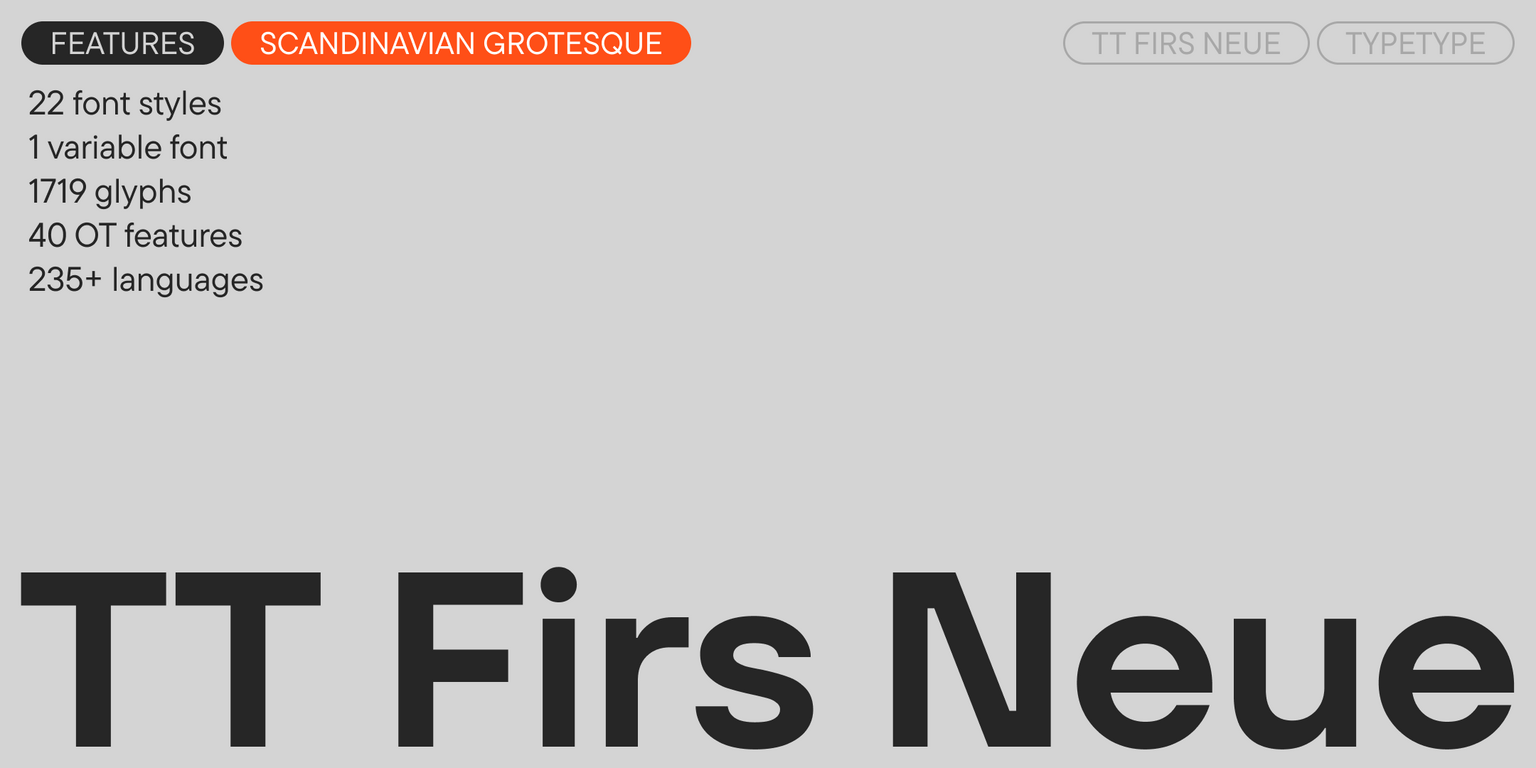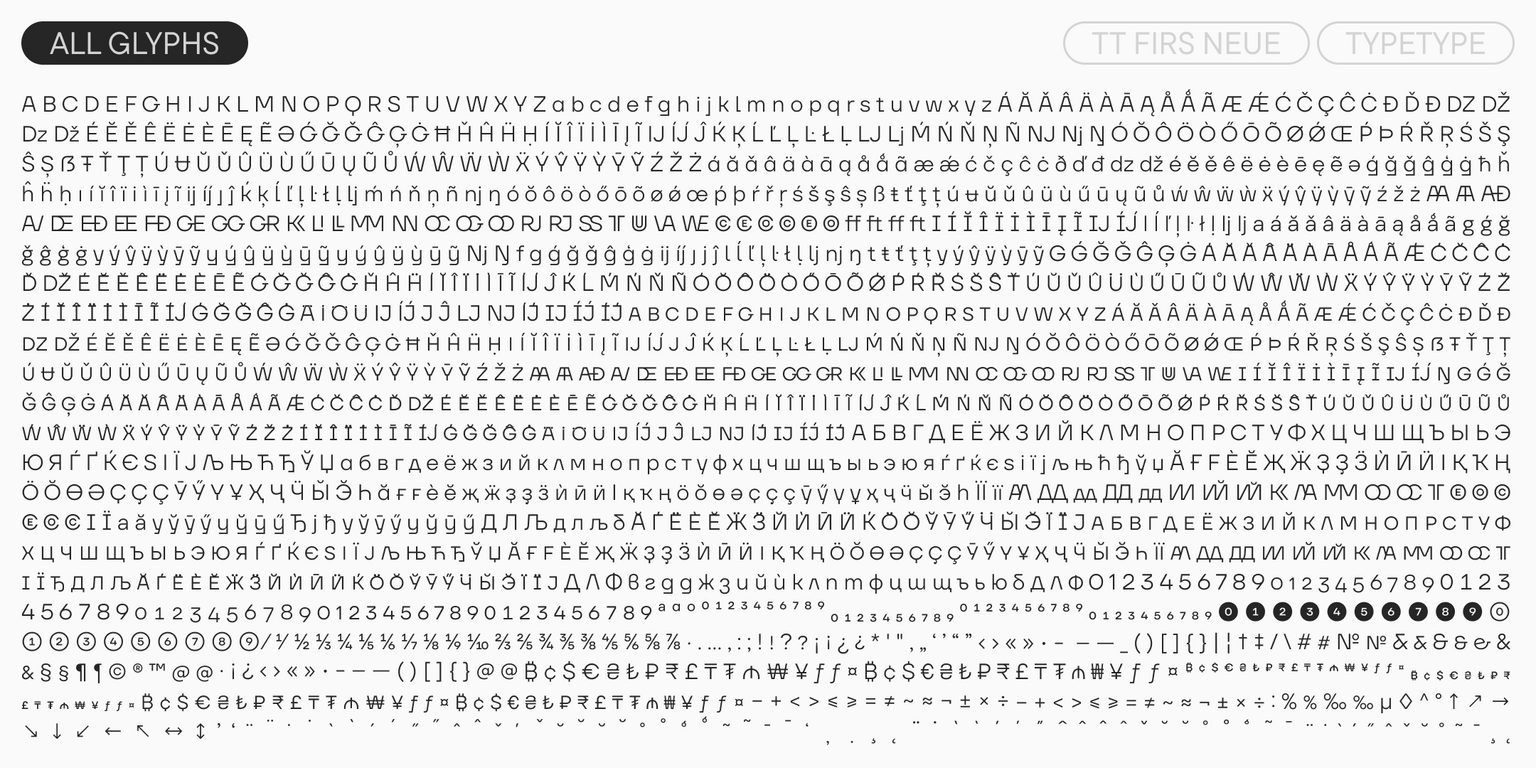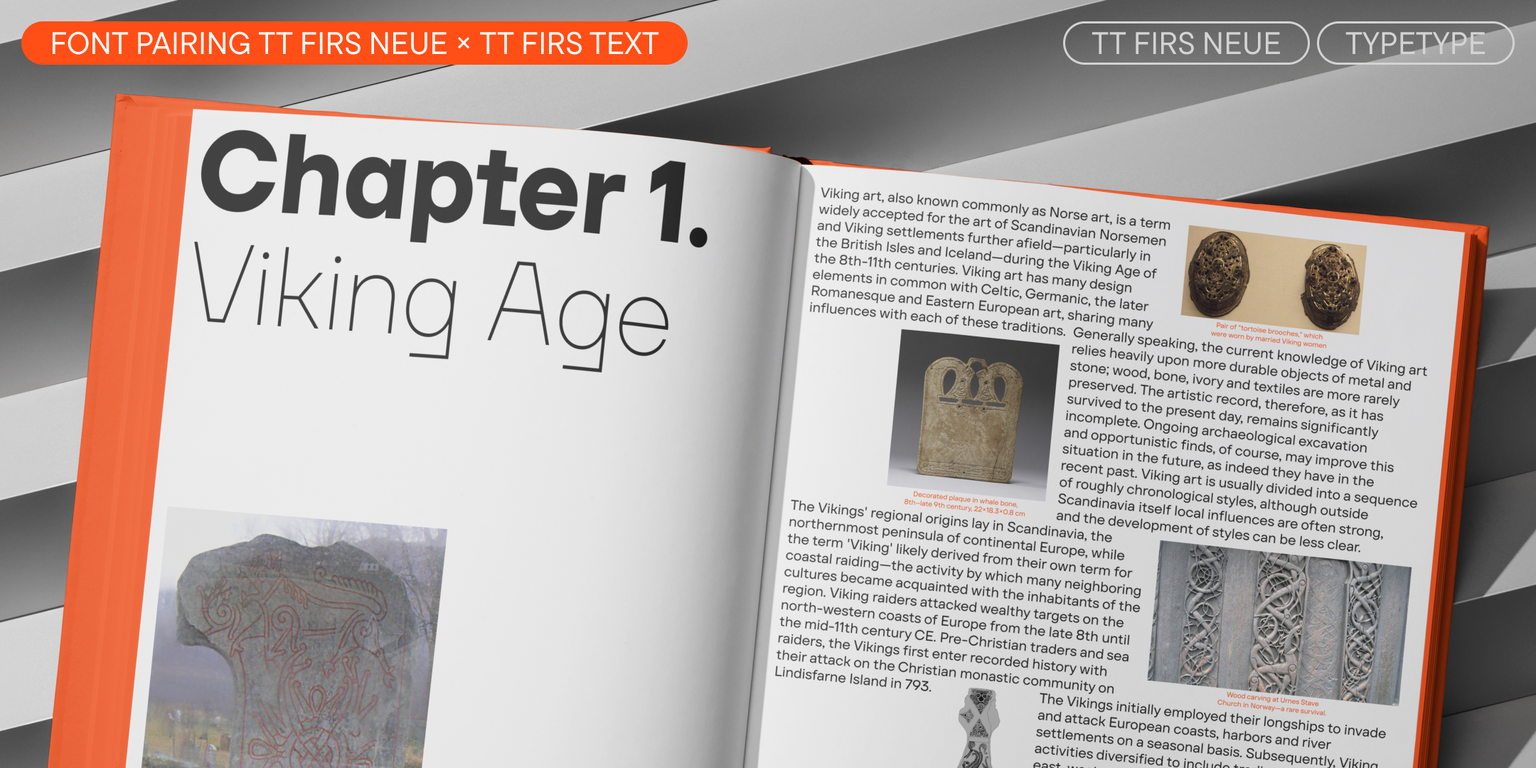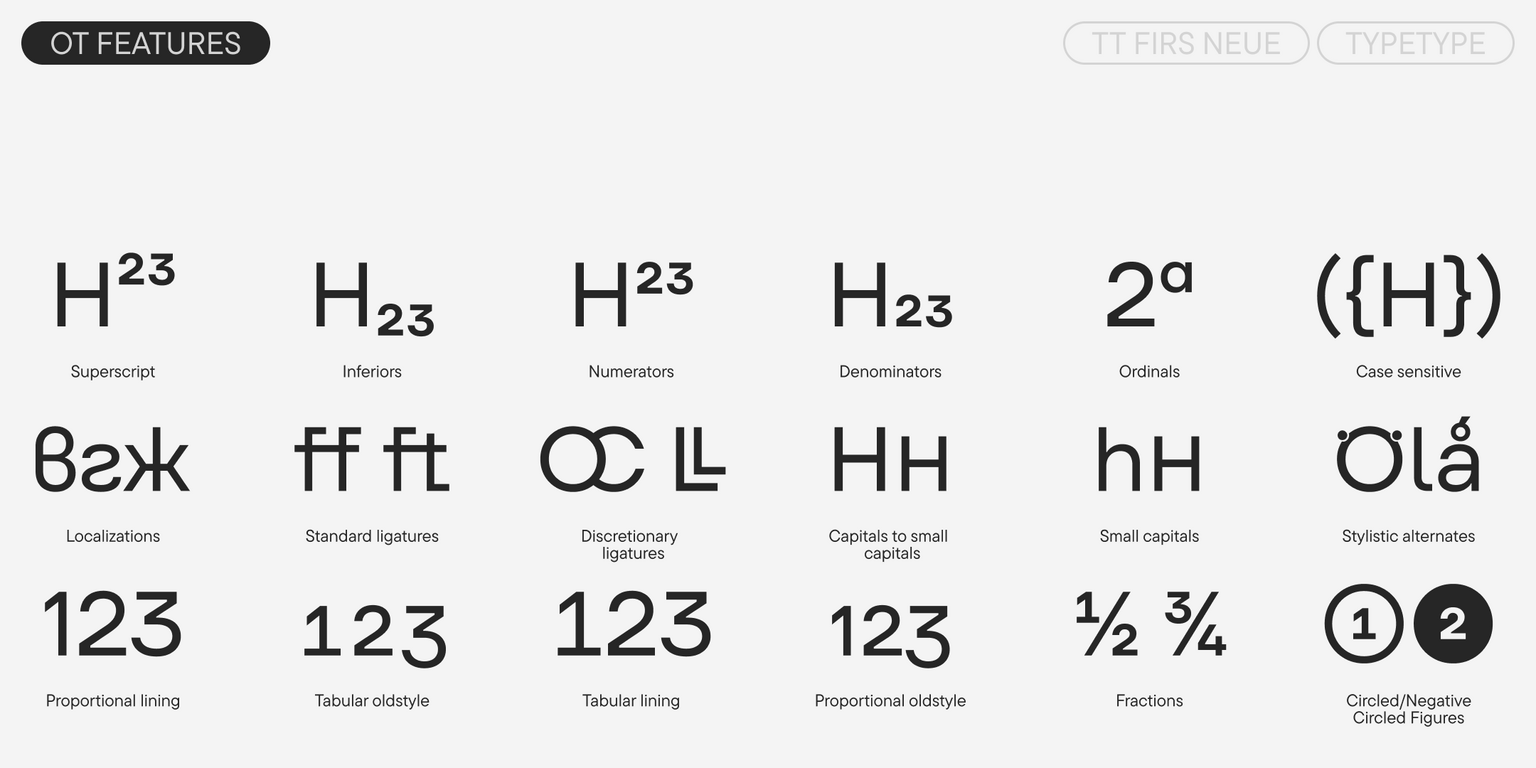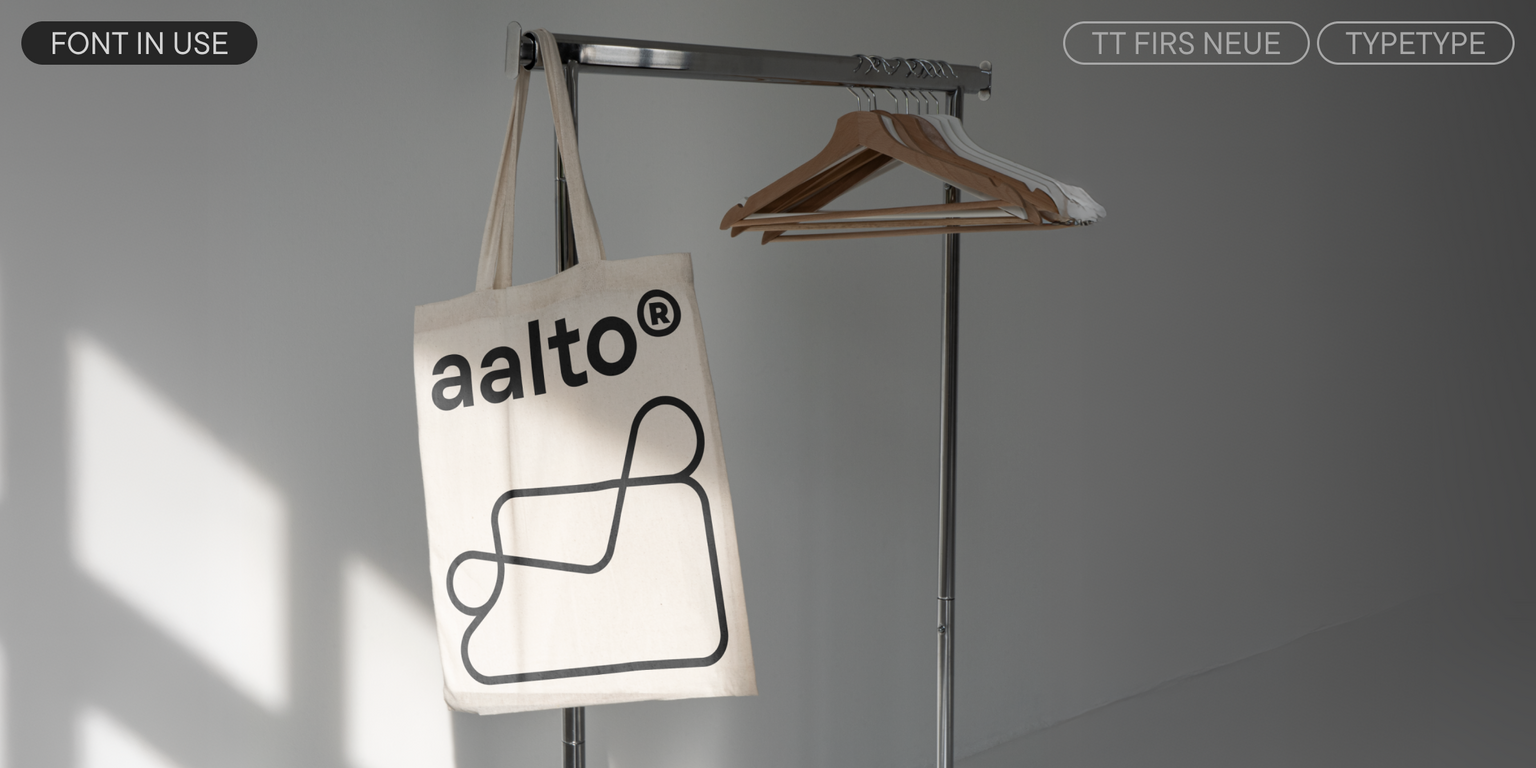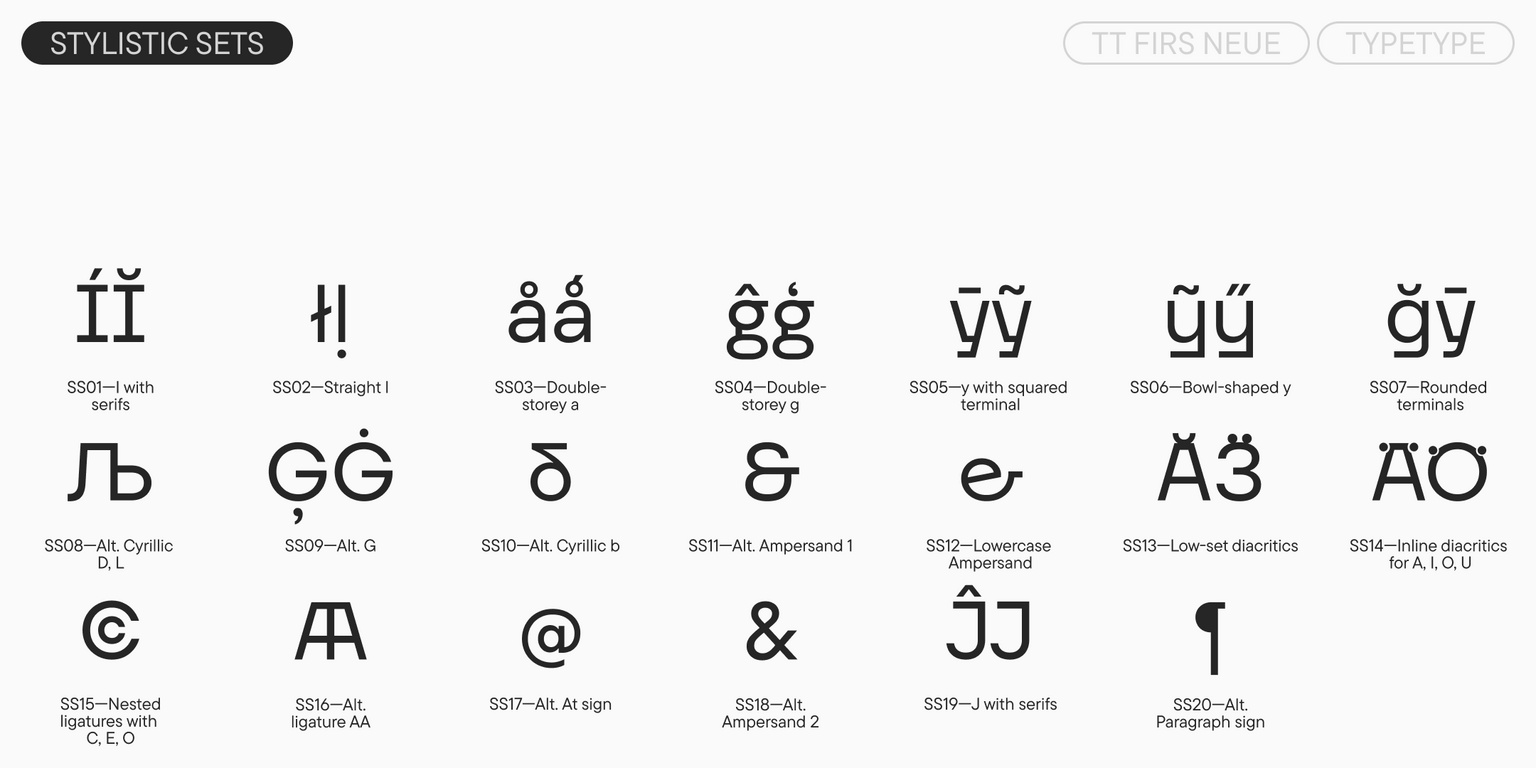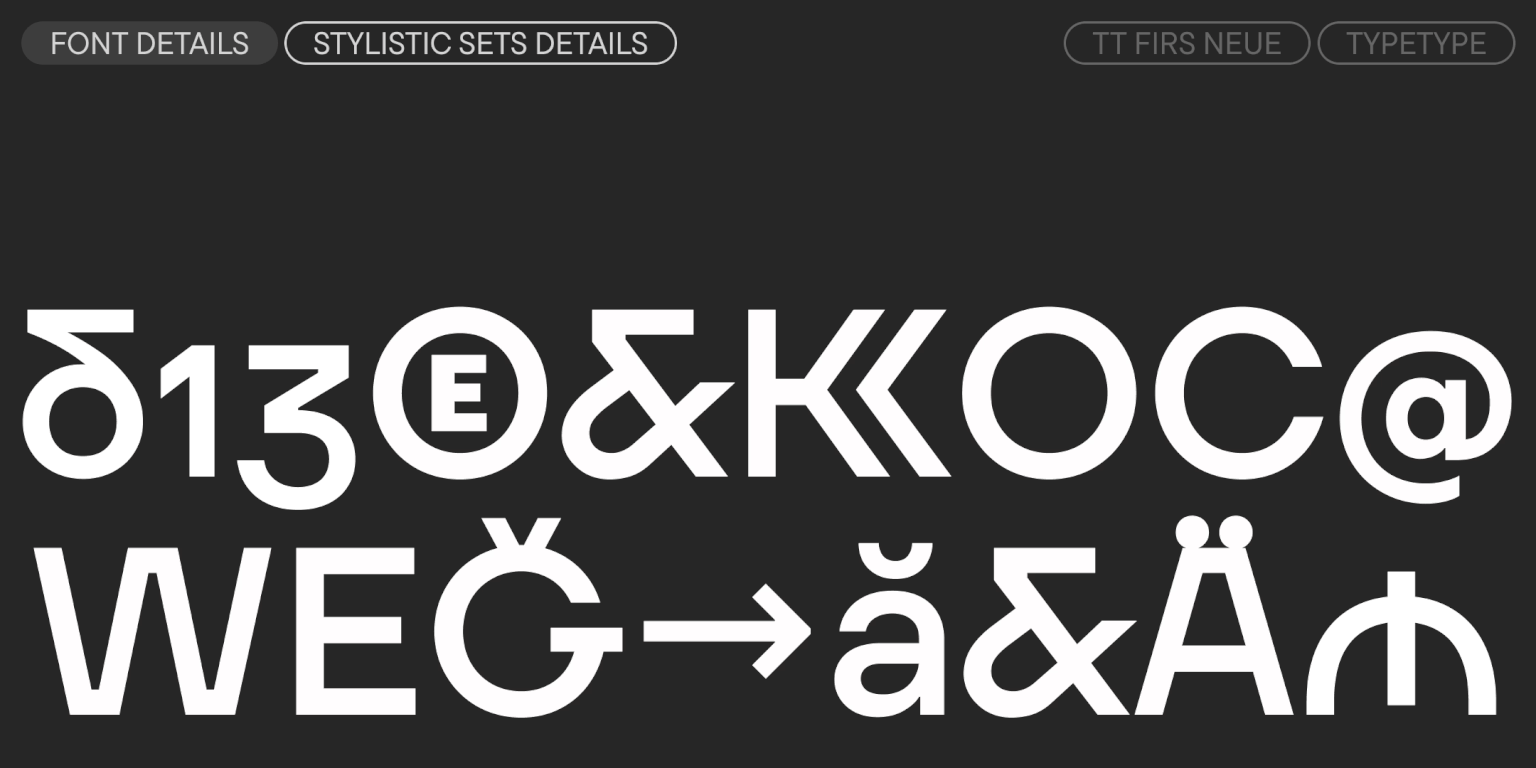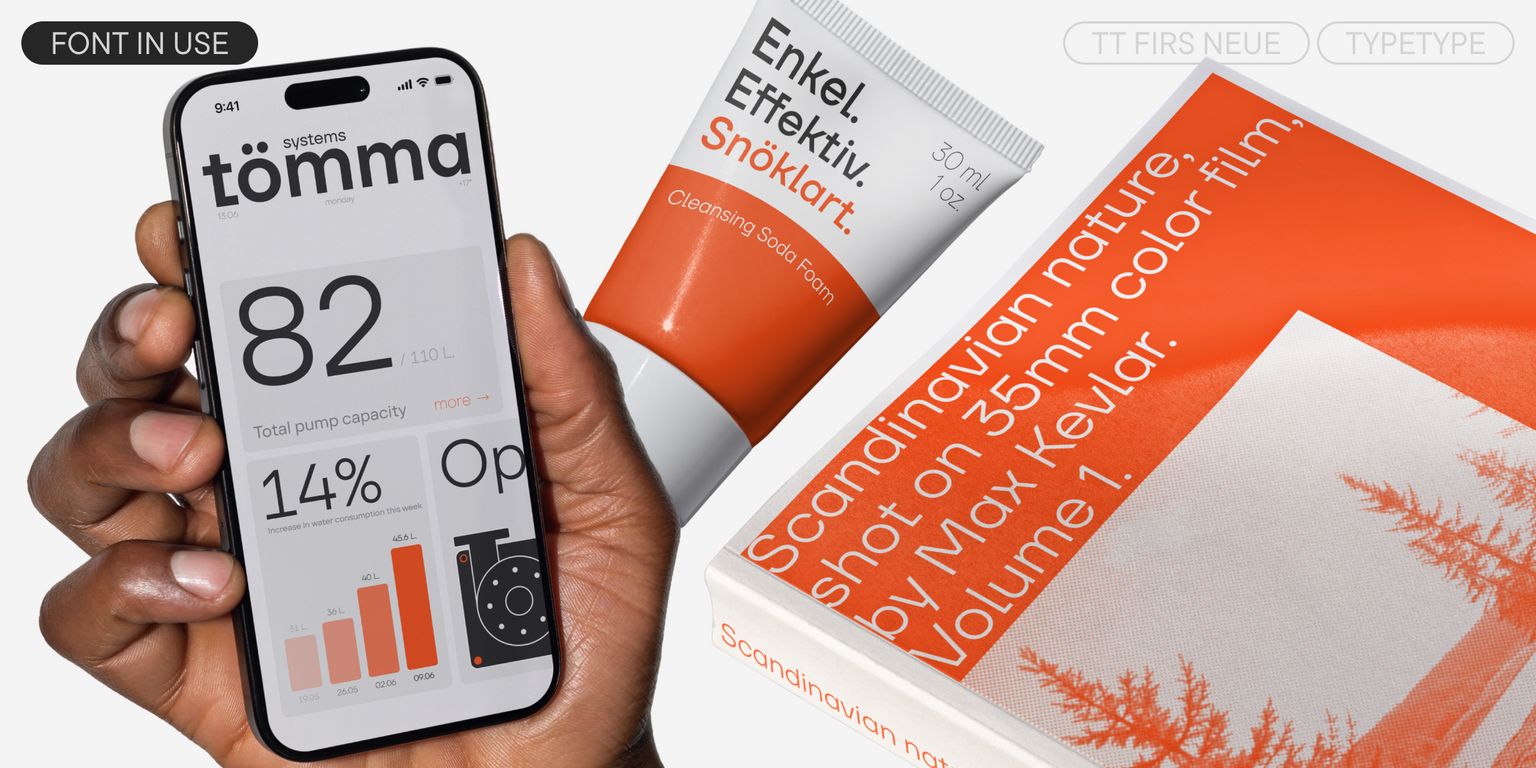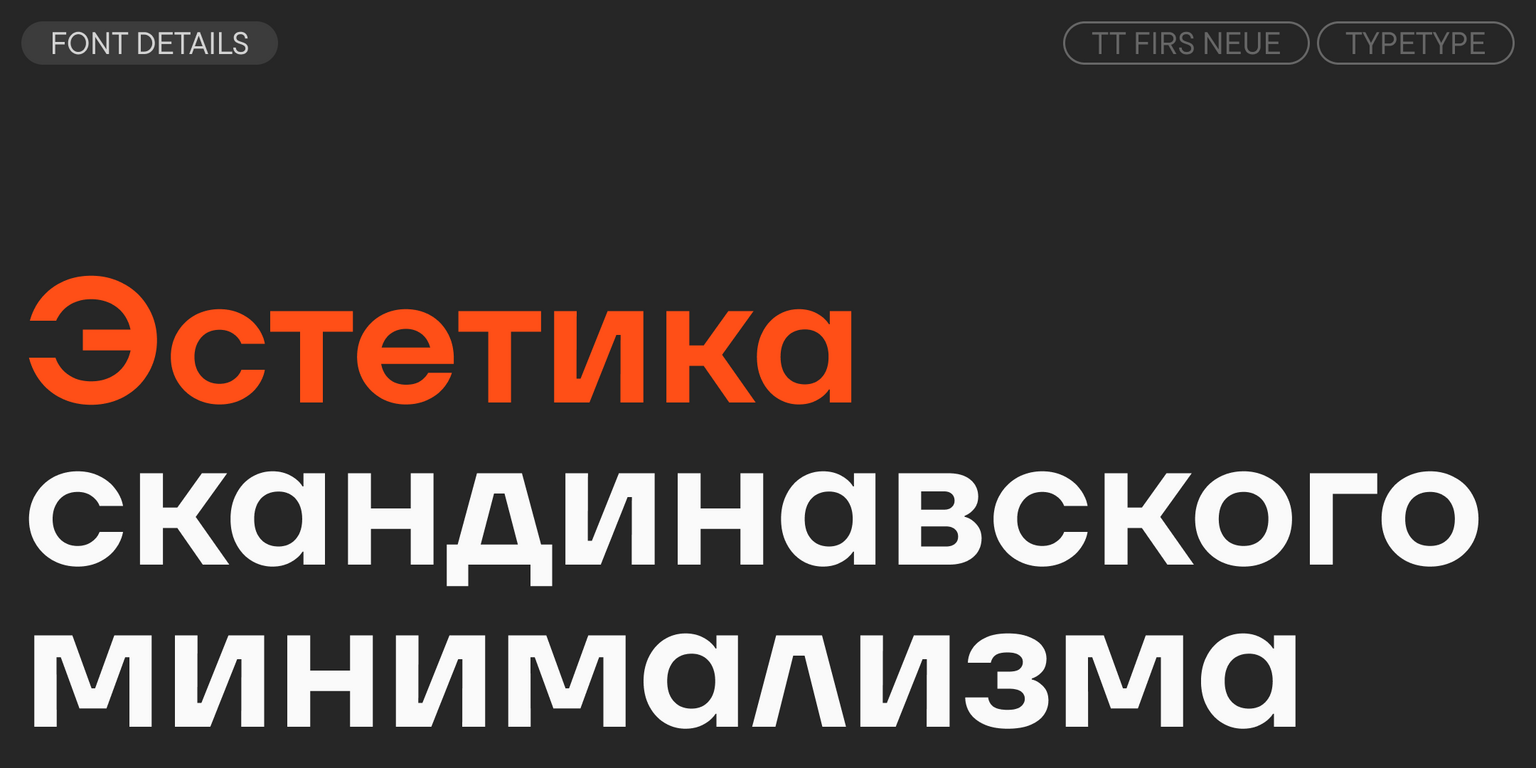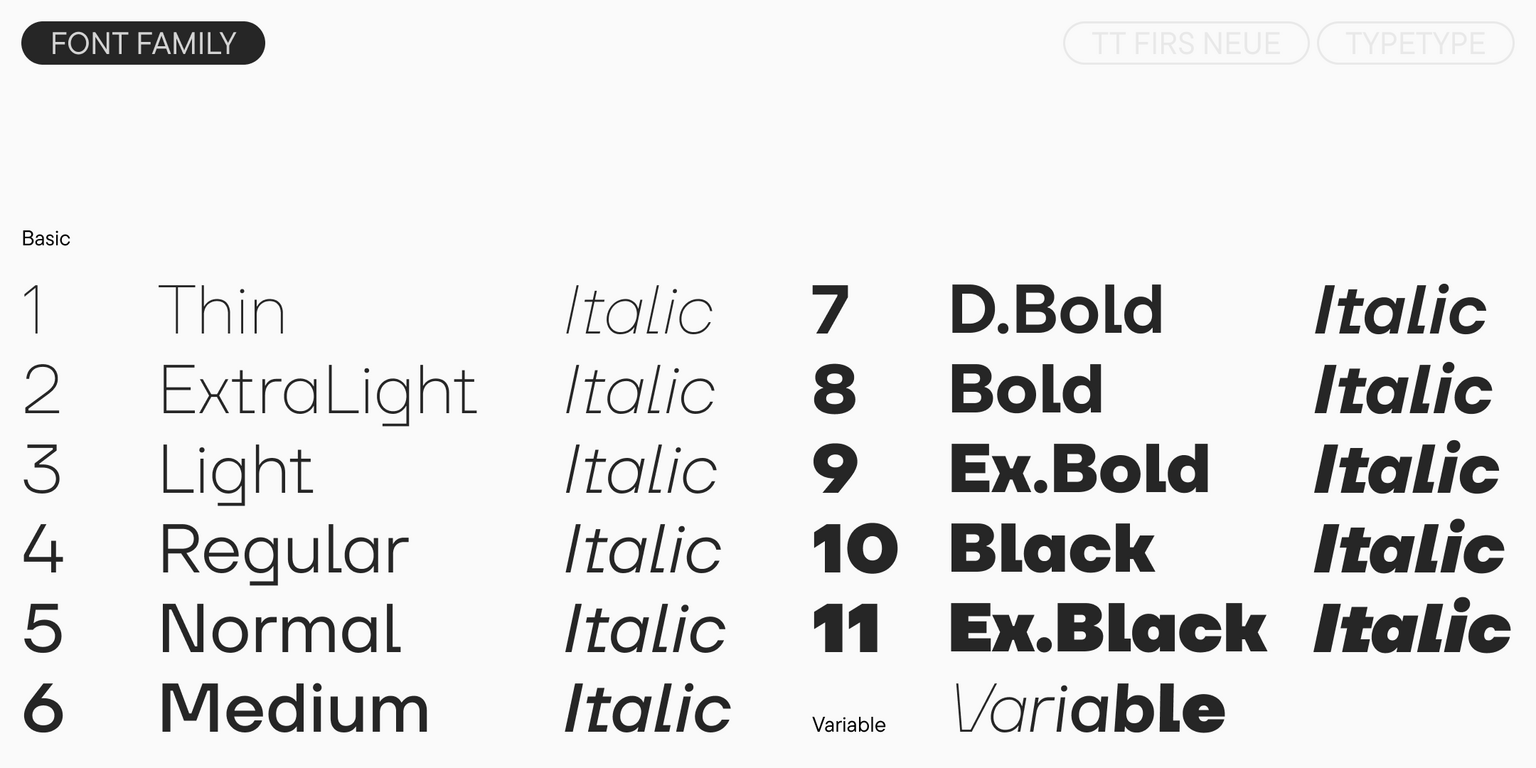
TT Firs Neue
TT Firs Neue — ТТ Фирс Нью
Произносится «ТТ Фирс Нью». «Фирс» — производное слово от fir, в переводе с английского «ель». «Neue» — в переводе с немецкого «новый». Буквы «TT» являются аббревиатурой названия компании.
TT Firs Neue — сбалансированный гротеск со скандинавскими мотивами. Это выразительный и привлекательный, при этом лаконичный и универсальный в использовании шрифт.
TT Firs Neue
TT Firs Neue — скандинавский гротеск с уникальными графическими элементами
TT Firs Neue
TT Firs Neue 2.0 берет свое начало в 2015 году, когда мы решили выпустить шрифт без засечек в скандинавском стиле под названием TT Firs. Три года спустя, в 2018 году мы переосмыслили и выпустили новую версию семейства шрифтов под названием TT Firs Neue. Вот лишь некоторые особенности нового семейства: более ярко выраженные акцидентные элементы шрифта, более крупные строчные символы и расширенный набор символов. После оглушительного успеха шрифта, в 2023 году, мы создали TT Firs Neue заново. В нем больше начертаний, набор символов увеличился вдвое, контуры и OpenType фичи стали более проработанными.
TT Firs Neue
Геометрический, самобытный, уникальный, универсальный
TT Firs Neue
Мы сделали совершенно новые италики
TT Firs Neue в дизайне
О гарнитуре TT Firs Neue
Встречайте TT Firs Neue версии 2.000 — скандинавский гротеск нового поколения!
TT Firs Neue — сбалансированный скандинавский гротеск с брутальным нордическим характером. Это узнаваемый и привлекательный шрифт, в котором выразительные графические элементы сочетаются с универсальностью использования. С момента выхода гарнитура приобрела огромную популярность среди дизайнеров, поэтому мы переиздавали её дважды — чтобы довести до совершенства. Подробную историю создания и развития TT Firs Neue рассказывали в статье.
Перед работой над обновлением мы провели масштабное визуальное исследование, чтобы сделать акцидентные детали привлекательными, а характер гарнитуры ещё более гармоничным. Так, визуальные компенсаторы в шрифте однородны по логике, а формы круглых знаков и знаков с полуовалами единообразны во всех начертаниях. Знаки с диагоналями, треугольные знаки и терминалы также приведены к единой логике. Шрифт выглядит консистентно и стилистически выверенно.
Также мы провели исследование по скандинавским языкам: это помогло создать аутентичные лигатуры и диакритические сеты, которые действительно будут полезны дизайнерам. Диакритика, цифры и знаки пунктуации придерживаются одной логики и способствуют гармоничному восприятию шрифта.
TT Firs Neue поддерживает большое количество полезных OpenType фич, в том числе альтернативные формы знаков. Также в гарнитуру входит вариативный шрифт, меняющийся по двум осям — жирности и наклону. Всё это позволяет подстраивать шрифт под свои задачи, открывая его с новых сторон.
TT Firs Neue — это шрифт-бестселлер, который пользуется большой популярностью, в том числе в европейском брендинге. Его можно увидеть в музеях, архитектурных бюро, кофейнях — он отлично вписывается в скандинавскую эстетику. TT Firs Neue может быть заголовочным или использоваться для фрагментов текста, подойдёт для брендинга или использования в вебе. Он эстетично выглядит на обложках подкастов или видеороликов, в оформлении витрин и вывесок, идеально подходит для создания айдентики и оформления упаковки.
TT Firs Neue — стильный минимализм со скандинавским послевкусием.
Alternative Cyrillic D, L
Low-set diacritics
onum | Oldstyle Figures
dlig | Discretionary Ligatures
case | Case Sensitive Forms